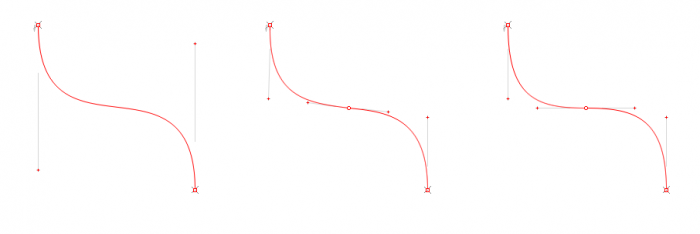
Fakt – komische S-Form oder Darstellungsfehler?
ich hab gerade bei Fontshop die »Fakt« (OurType) ausprobiert und mir kommen die Formen des Versal-S sehr, sehr komisch vor (siehe Anhang & https://www.fontshop.com/tryout?referer=/families/fakt). Ich frage mich, ob diese Formen so wirklich in der Schrift enthalten sind oder ob das ein Darstellungsfehler der Fontshop-Vorschau ist.
Auf dieser Seite (http://www.typografie.info/3/page/Schriften/fonts.html/_/fakt-r344) sind zwei Versal-S aufgeführt. In der kleinen Größe kann ich die exakte Form aber nicht so wirklich erkennen. Sieht aber eher danach aus, dass die Form nicht so aussieht wie bei Fontshop.
Hat da jemand eine Info parat?
Auf die FontShop-Vorschau würde ich nicht so viel geben. Da hakt es des Öfteren mal, besonders bei geschwungenen Formen.
Schau mal in die Schriftmuster-PDF. Solltest Du immer noch Zweifel haben, kannst Du Dich auch direkt an Ourtype wenden und dort um eine Demo-Version bitten. Möglicherweise kommt man dieser Anfrage nach.
Danke für den Link zum PDF. Dort sieht das S sehr gut aus. Scheint an dem Fontshop-Tool zu liegen. Hab schon einen Schreck bekommen.
Ich habe da so einen Verdacht, da mir ein etwas (wenn auch nicht so schlimmes) eierigwerden bei diesen Vorschauen schon öfter aufgefallen ist. Es könnte an der Lage der Knoten im S liegen:
Wenn ich also dieses verdammte S zeichnen will, erzeuge vich einen schön glatten S-Bogen zumeist wie im ersten Beispiel, also ein Kurvenabschnitt mit 2 Kontrollvektoren, die eben solch eine Linie mit Richtungswechsel erzeugen. Lasse ich das im Font so, funktioniert das als Font auch prima.
Führe ich jedoch ein Font-Audit nach generellen Fehlern durch, wird eine solche Kurve angemeckert, und auch in den Anleitungen der Font-Editoren steht, dass solche Kurven zu vermeiden sind. Also wird an dem Wendepunkt der vKurve ein zusätzlicher Knoten eingefügt, mit wieder eigenen Kontrollvektoren. Im exportierten Font ändert das erst einmal nichts.
Wenn ich diesen Font aber durch ein Programm kurbele, das daraus die verschiedenen Webfont-Formate macht, scheint duieses aber zum einen den UPM-Wert zu normalisieren, bersonders wenn dieser von den üblichen 1000 (bei Postscript) oder 2048 (bei Truetype) abweicht, und zusätzlich scheint es dabei auch ein Cleanup der Konturen zu geben, um Fonts mit extensiven Knoten in ein kleineres Dateiformat zu bekommen.
Liegen dan n aber die Kontrollvektoren dieses Wendepunktes recht nah an deer Waagerechten, kann es passieren, dass diese in die Waagerechte gezogen werden, und dabei mit den Kontrollpunkten auch noch auf einen glatten UPM-Wert gerundet werden, das führt dann zur eierigen Kurve im dritten Beispiel.
Ich habe mir vor ein paar Tagen die Meret von Ourtype bei Fontshop angeschaut um die Preise zu vergleichen. Dabei wurde ein Schnitt komplett durch eine völlig andere Schrift ersetzt. Da scheint es also technische Probleme zu geben ...
Übrigens sehr schön, dass die Fakt für C, G, J, K, M, Q, R und S alternative Versionen bietet.
:nicken: Sogar bei den Gemeinen herrscht Artenvielfalt. ;-)
Laut OurType wollte Thomas Thiemlich sogar das Beste der beiden Klassiker in einer Schrift vereinen. Jedoch nicht über formale Interpolation, sondern mittels Stylistic Sets, welche die statische Grotesk (Standardbelegung) in eine geometrische Serifenlose verwandeln. Damit erhält der Anwender zwei Formprinzipien in einer Schrift.
Die Frage ist bloß, was sicher besser vermarkten lässt: eine Schrift, in der die zweite versteckt wurde oder zwei Einzelschriften, bei der die formalen Unterschiede sofort erkennbar sind.  :-?